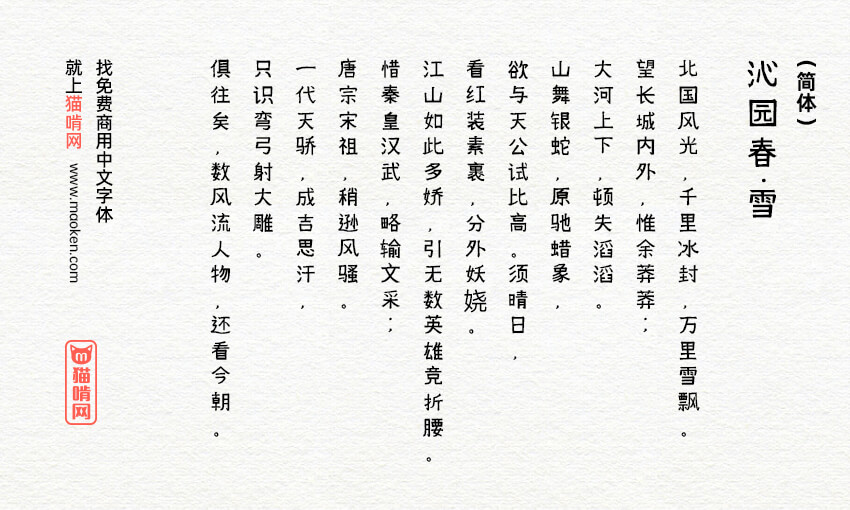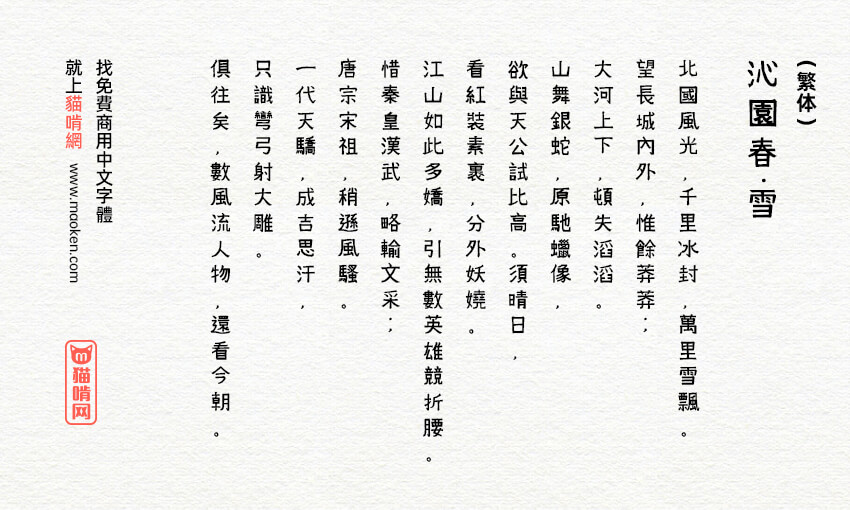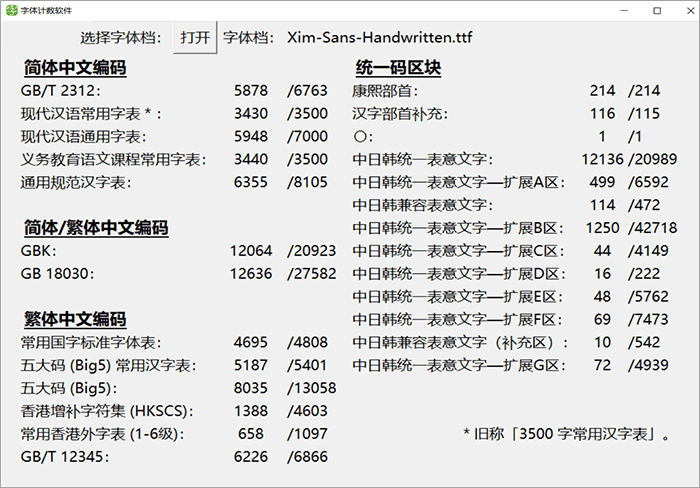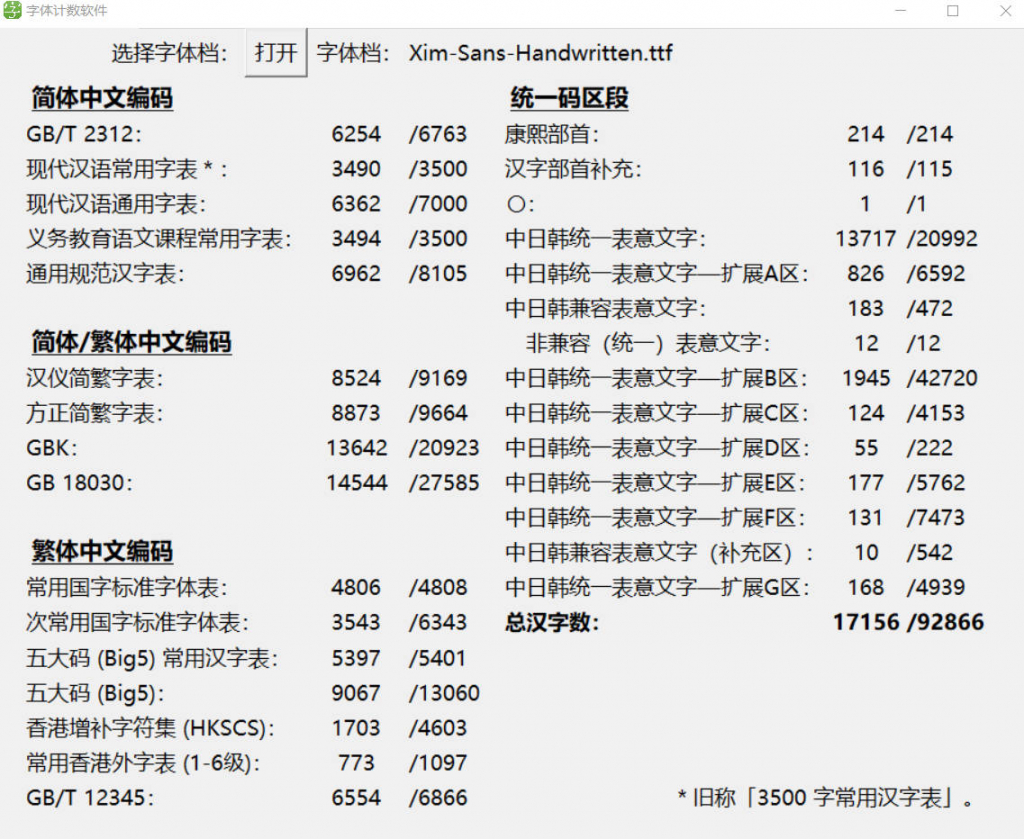
Xim Sans手写体(日文名:Xim Sans 手書き風)是日本设计师ximco创作的一款免费商用手写字体。这款手写字体的风格,据作者自己称“它有一种恐怖的味道”。现在收录43,760文字,我的目标是世界上记录字符数最多的字体!
这次是第一次用fontforge编辑,所以我觉得这是一个对我来说迈出了一大步的版本。 (版本号也是1.30,不错)。特别感谢Dare-demo Iie.ttf(叛逆Mincho的人)通过操作fontforge告诉我我不明白的事情。
简体模式下 誕 和 延 码位反了
管理员,在1.43版本中,中国《通用规范汉字表》中的简体字已超过7000个!! (这可能是因为提到这个字体支持中文吗?)
这款日文字体对简体字支持比较好,但是在1.38版本中,增加了“韡”的简繁体……(中国 Lxgw 也经常为这个字符添加简体字,但是如果你使用这个日文字体的 1.38 版本…“哦!!添加了‘韡’这个非官方的简体字,所以我可以放心地使用这个日文字体了。”)
作为一款日文手写字体,这个字体对中文简体字的支持比较好,所以作为系统字体很好用!!但是,缺少一些简体字,原作者不想要求额外的文字!但我真的很期待1.37版!!
在我看来,Xim sans 1.37 版中添加的汉字列表包括我几个月前要求的标准汉字表中的一些汉字,其余的以 Unicode 注册的汉字,以及其余的简体人物!!也就是说,在这个版本中,中国标准汉字表中的部分汉字也可以使用了!!